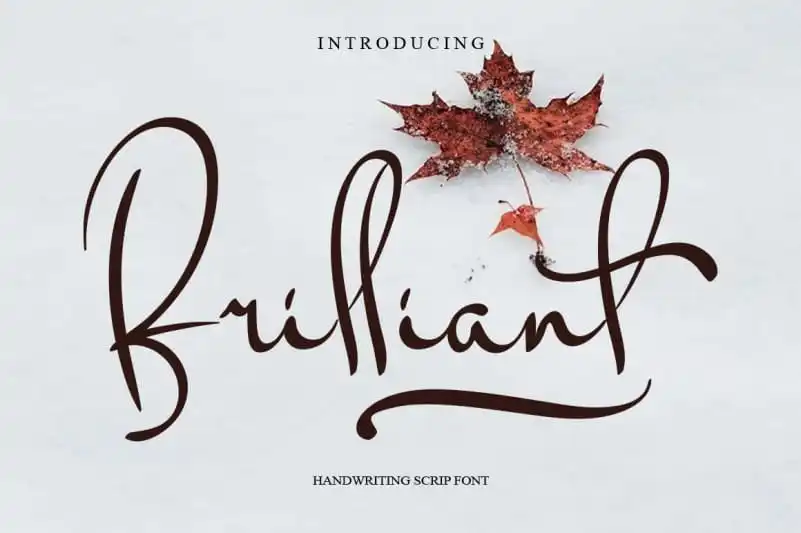
Brilliant Script Font – Fonte Grátis
Brilliant Script Font
A fonte ‘Brilliant Script Font’ é uma elegante escolha para aqueles que buscam um toque delicado e suave no design. Desenvolvida pelo designer levincreative, essa fonte escrita a mão cai bem em diversas ideias de projeto. Com seu traço fino e curvilíneo, esta fonte tem um aspecto encantador que fará seus projetos brilharem ainda mais. Seja para criar uma cartinha romântica ou um design minimalista moderno, a ‘Brilliant Script Font’ trará sua própria dose de leveza e alegria à sua arte. Um verdadeiro complemento perfeito para qualquer trabalho de design criativo.